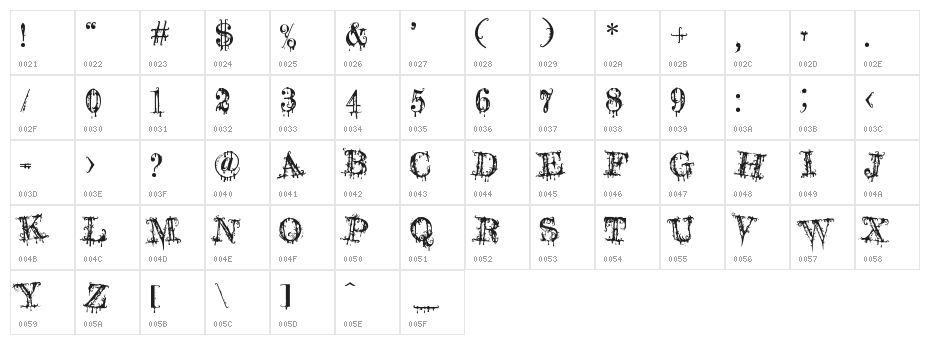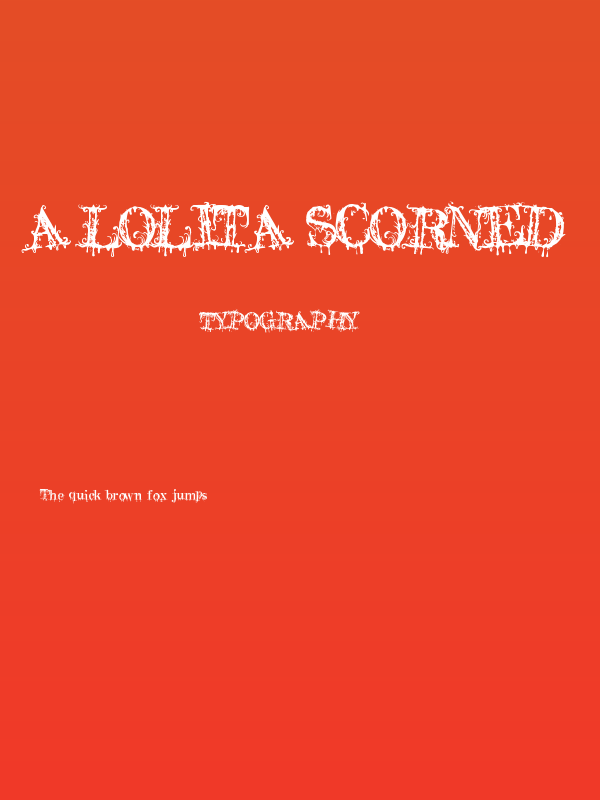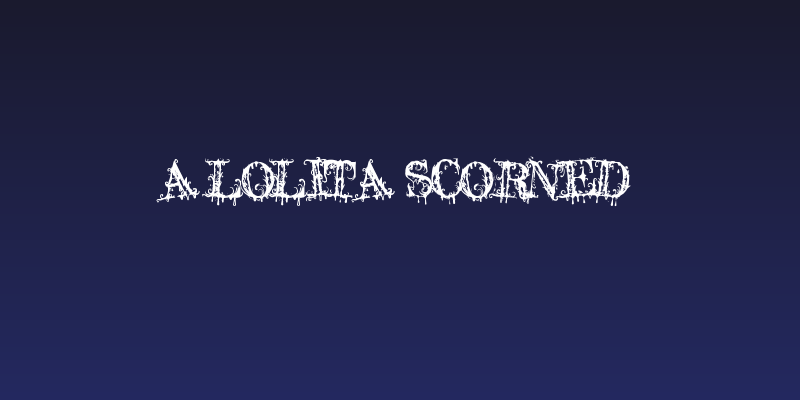
A Lolita Scorned Font
| Категория | Horror |
| Общий стиль | Gothic, Decorative |
| Область применения | Headlines, Posters, Logos |
| Рекомендуемые проекты | Ideal for Halloween-themed projects, horror movie posters, gothic event invitations, and edgy graphic designs. |
A Lolita Scorned